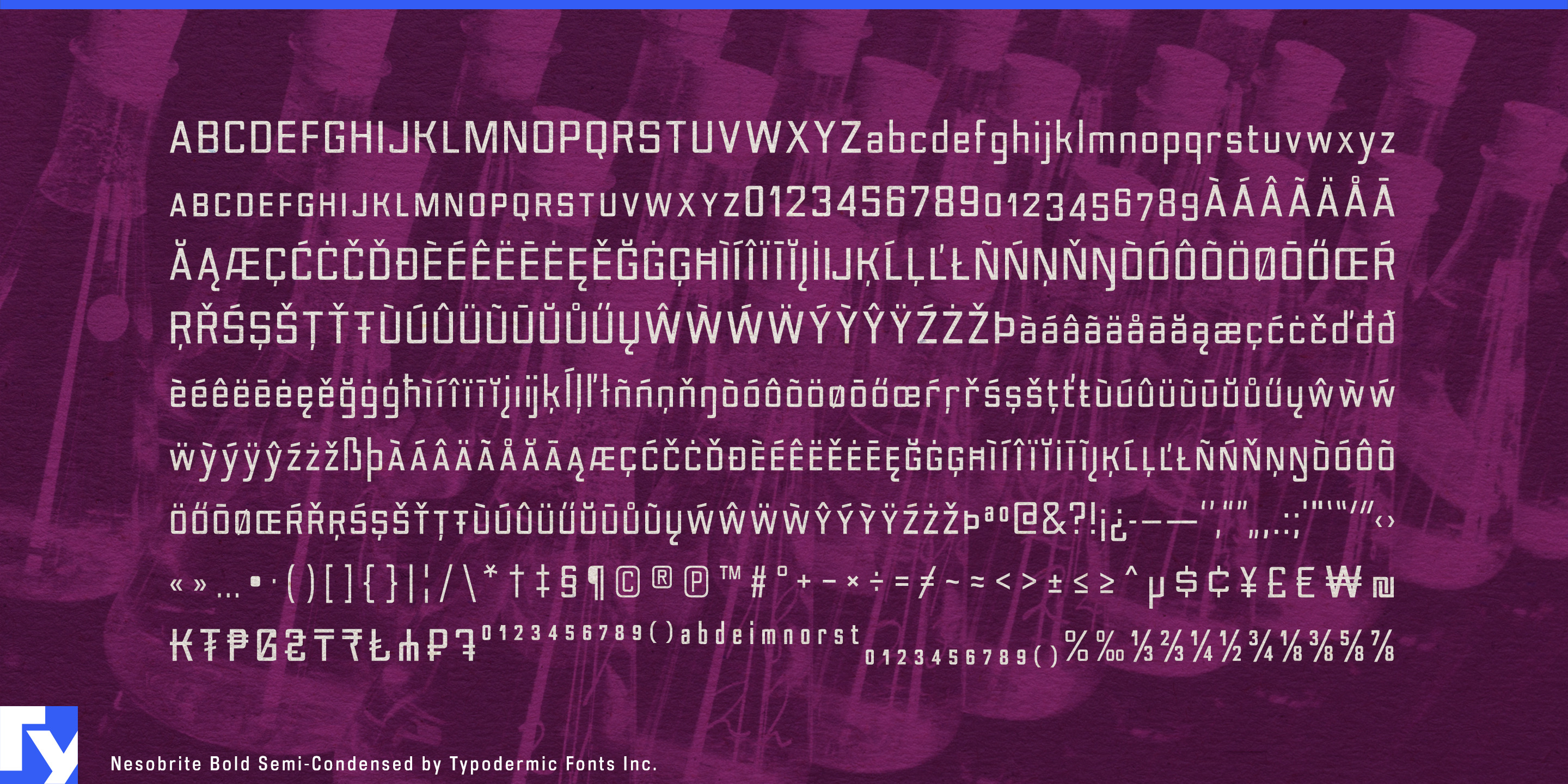
Nesobrite
Technische Typografie profitiert nicht immer davon, kräftiger zu werden. Auf einer Instrumententafel, in einem Laborsystem, einer Diagnoseoberfläche oder einem Präzisionsgerät kann ein übergroß gesetzter Black-Schnitt die Messwerte, Diagramme, Bedienelemente und Statusangaben übertönen, auf die es eigentlich ankommt. Nesobrite verfolgt einen gemäßigteren Ansatz. Ihre rechtwinklig aufgebaute Konstruktion schafft eine starke technologische Identität, doch selbst die dunkelsten Schnitte bleiben vergleichsweise offen und erzeugen Betonung, ohne jede Überschrift in einen Tintenblock zu verwandeln.
Starre Vertikalen, rechtwinklig aufgebaute Buchstabenbäuche, eine hohe x-Höhe und modulare Formen verleihen Wörtern einen technisch entwickelten Rhythmus. Mehrere Breiten und passende Kursive lassen diese Struktur an Gerätefronten, schmale Modellnamen, Präsentationsgrafiken, Softwareüberschriften und technische Diagramme anpassen. Das Spektrum reicht von feiner analytischer Displaytypografie bis zu kontrollierter kräftiger Betonung, statt extremen Strichstärken nachzujagen.
Laborautomation und wissenschaftliche Geräte sind besonders natürliche Einsatzfelder. Probenhandhabungssysteme, Chromatografieanlagen, Spektroskopiegeräte, Umweltanalysatoren, Materialprüfgeräte und Laborroboter brauchen Typografie für Modellnamen, Plattformbezeichnungen, Touchscreen-Überschriften, technische Broschüren und Konferenzdisplays. Nesobrite kann die Gerätefamilie kennzeichnen, ohne mit Grafiken, Messwerten, Bedienelementen und anderen funktionalen Informationen zu konkurrieren.
Die Biotechnologie überträgt dieselbe Sprache auf Zellanalyseplattformen, Sequenziersysteme, Werkzeuge der synthetischen Biologie, automatisierte Bioprozessierung und Labordatensysteme. Halbleiterprüfung und Präzisionselektronik sind ein weiteres starkes Einsatzfeld: Wafer-Inspektionssysteme, Messplätze, Photonikgeräte, HF-Messtechnik, Kalibriersysteme und Präzisionsnetzteile verbinden oft lange Modellnamen mit schmalen Bedienfeldern und dichten Diagrammen. Dank Nesobrites Breitenspektrum lassen sich diese Namen bei Bedarf komprimieren, ohne das größere visuelle System zu verlassen.
Der Raumfahrtbetrieb ist ein verwandtes Gebiet, das keine Science-Fiction-Theatralik braucht. Satellitensteuerungen, Telemetrieplattformen, Bodenstationen, Ortungsgeräte, Erdbeobachtungssysteme und Raumfahrzeugtests brauchen alle Namen von Teilsystemen, Statusüberschriften, Gerätebeschriftungen, Missionsgrafiken und technische Präsentationen. Medizinprodukte, Gebäudeautomation, Prozessüberwachung und Umweltregelsysteme können dieselbe zurückhaltende technische Stimme nutzen.
In der Unterhaltung kann Nesobrite von Technik zu Abläufen wechseln. Forensikthriller, Überwachungsdramen, wissenschaftliche Rätselgeschichten und Ermittlungsspiele können ihre schmaleren Schnitte für Fallnummern, Überschriften in Beweissystemen, Kartenüberlagerungen, Aktengrafiken und analytische Benutzeroberflächen einsetzen.
Nesobrite ist nicht um brachiale Displaystärke herum gebaut. Ihre Stärke liegt in kontrollierter Betonung: eine technisch konstruierte Displaystimme für Labore, Präzisionselektronik, Raumfahrtbetrieb, Medizinprodukte, industrielle Steuerungen und andere informationsreiche technische Umgebungen.